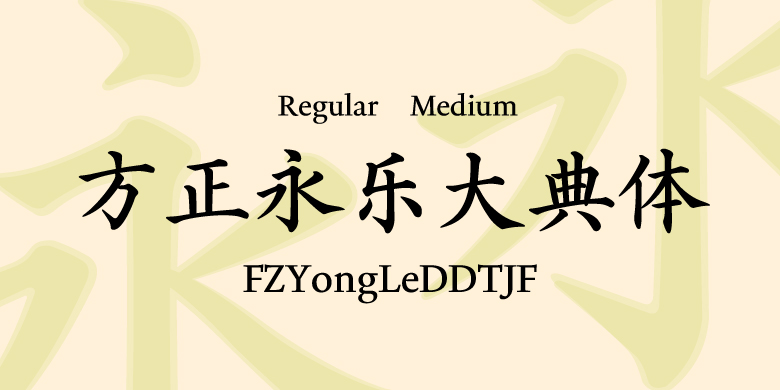
方正永乐大典体
汪文,何诗旸
楷书
方正永乐大典字体是基于中国国家图书馆所藏《永乐大典》珍贵原件进行的系统性数字化复刻。该字体汲取了宫廷抄写官笔下的“台阁体”神髓,字形端庄整肃,笔划丰润遒劲,结构严谨匀停,充分体现了明代官方楷书的法度与气象。作为对这部规模冠绝古今的典籍宝库的深情致敬,此款字体的开发不仅填补了明朝官方书体数字化研究的空白,更让仅存四百余册的瑰宝笔墨得以在数字媒介中重焕新生。字库设计兼顾简繁中文与多文种排版,使这份穿越六百年的典雅墨韵,能为当代设计注入深厚的文化底蕴与历史厚重感。